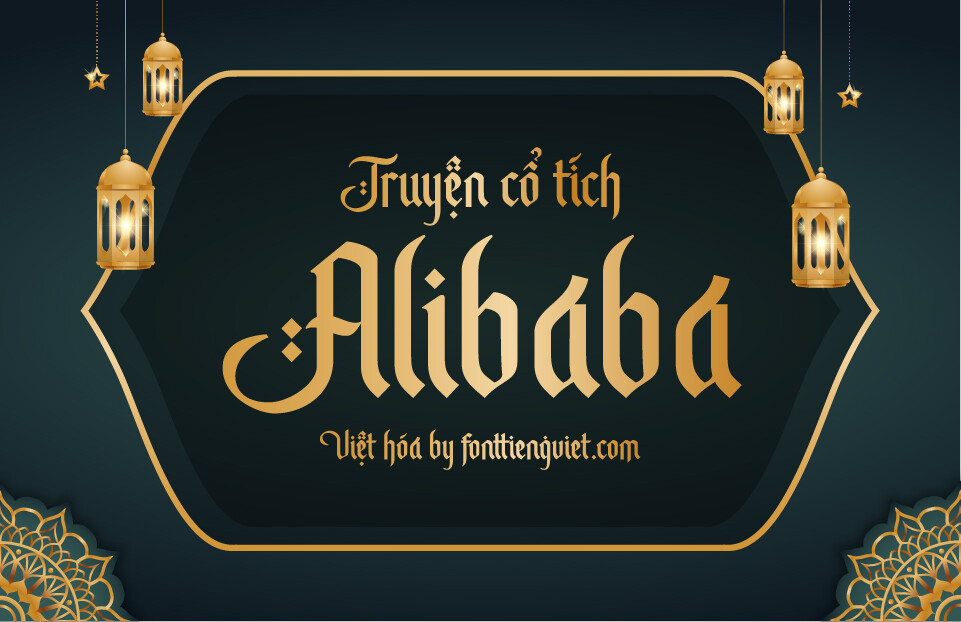
Font Việt hóa 1FTV VIP Kahfi
Giới thiệu về Font Việt hóa 1FTV VIP Kahfi
Trong thế giới thiết kế đồ họa hiện đại, việc lựa chọn một Font Miễn Phí phù hợp đóng vai trò quan trọng trong việc truyền tải thông điệp. Font Việt hóa 1FTV VIP Kahfi là một trong những bộ phông chữ độc đáo, mang phong cách thư pháp Ả Rập (Arabic) nhưng đã được tinh chỉnh để phục vụ người dùng Việt Nam. Với các đường nét uyển chuyển và đậm chất nghệ thuật, bộ phông này giúp các tác phẩm trở nên ấn tượng và có chiều sâu văn hóa hơn bao giờ hết.
Đặc điểm nổi bật của Font Việt hóa 1FTV VIP Kahfi
Bộ phông chữ này sở hữu cấu trúc các nét dày mỏng đan xen nhịp nhàng, tạo cảm giác mềm mại nhưng vẫn giữ được sự mạnh mẽ cần thiết. Font Việt hóa 1FTV VIP Kahfi đã được xử lý kỹ lưỡng về bảng mã, giúp người dùng gõ tiếng Việt có dấu mà không lo bị lỗi hiển thị. Đây là lựa chọn lý tưởng cho các bạn học sinh làm báo tường, giáo viên thiết kế bài giảng điện tử hoặc các nhà thiết kế tạo dựng biểu trưng và tiêu đề sách.
Cách sử dụng Font Việt hóa 1FTV VIP Kahfi trong thực tế
Để phát huy tối đa vẻ đẹp của phông chữ này, bạn nên kết hợp nó với các màu sắc trung tính hoặc tông màu trầm như vàng đồng, nâu đất. Font Việt hóa 1FTV VIP Kahfi cực kỳ hiệu quả khi dùng làm headline cho các bìa menu, thiệp mời sự kiện hoặc các ấn phẩm mang hơi hướng cổ điển. Sự khác biệt về hình khối của chữ sẽ ngay lập tức thu hút thị giác của người xem, tạo nên dấu ấn riêng biệt cho sản phẩm của bạn.
Kết luận về bộ font chữ độc đáo